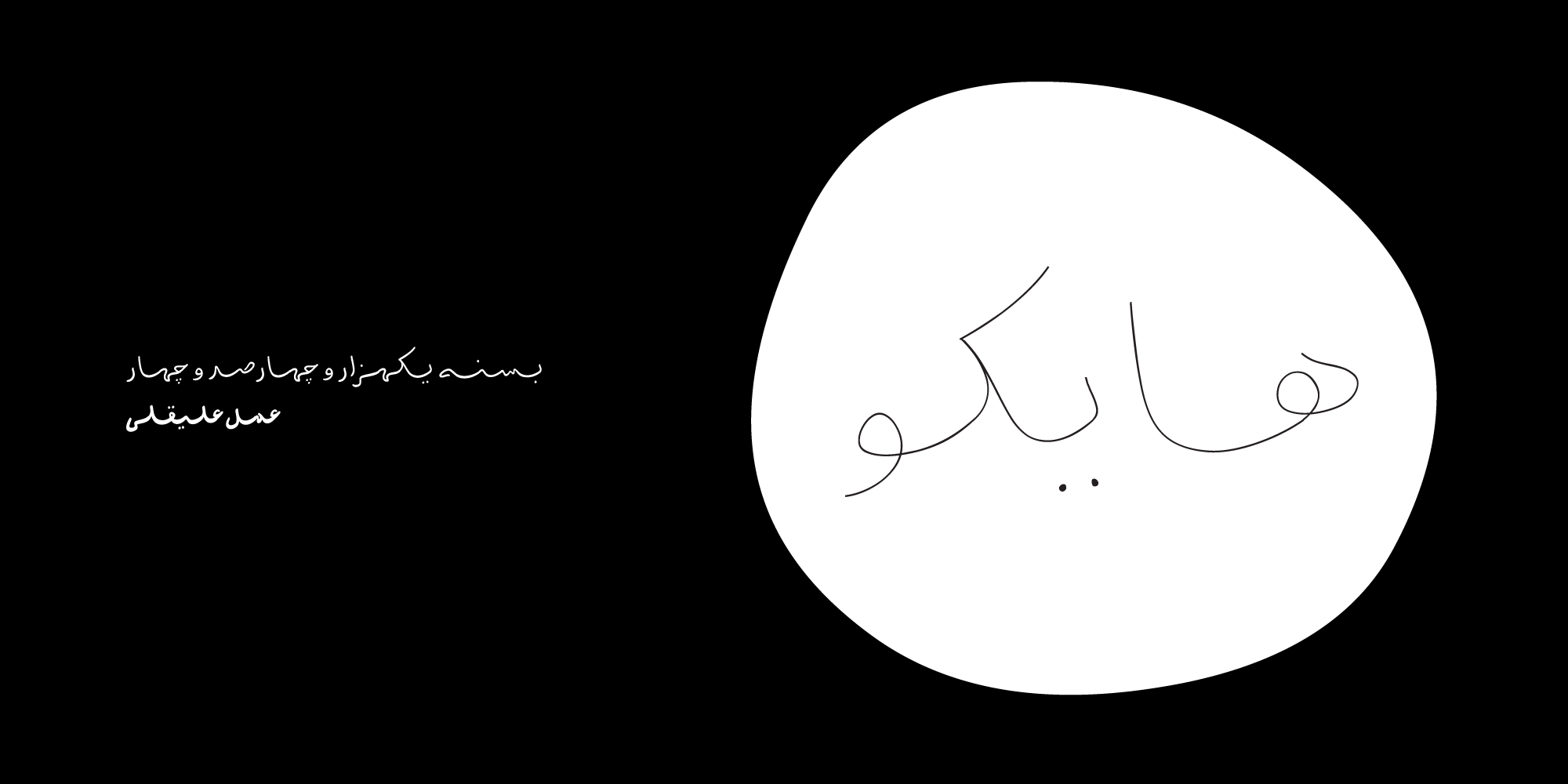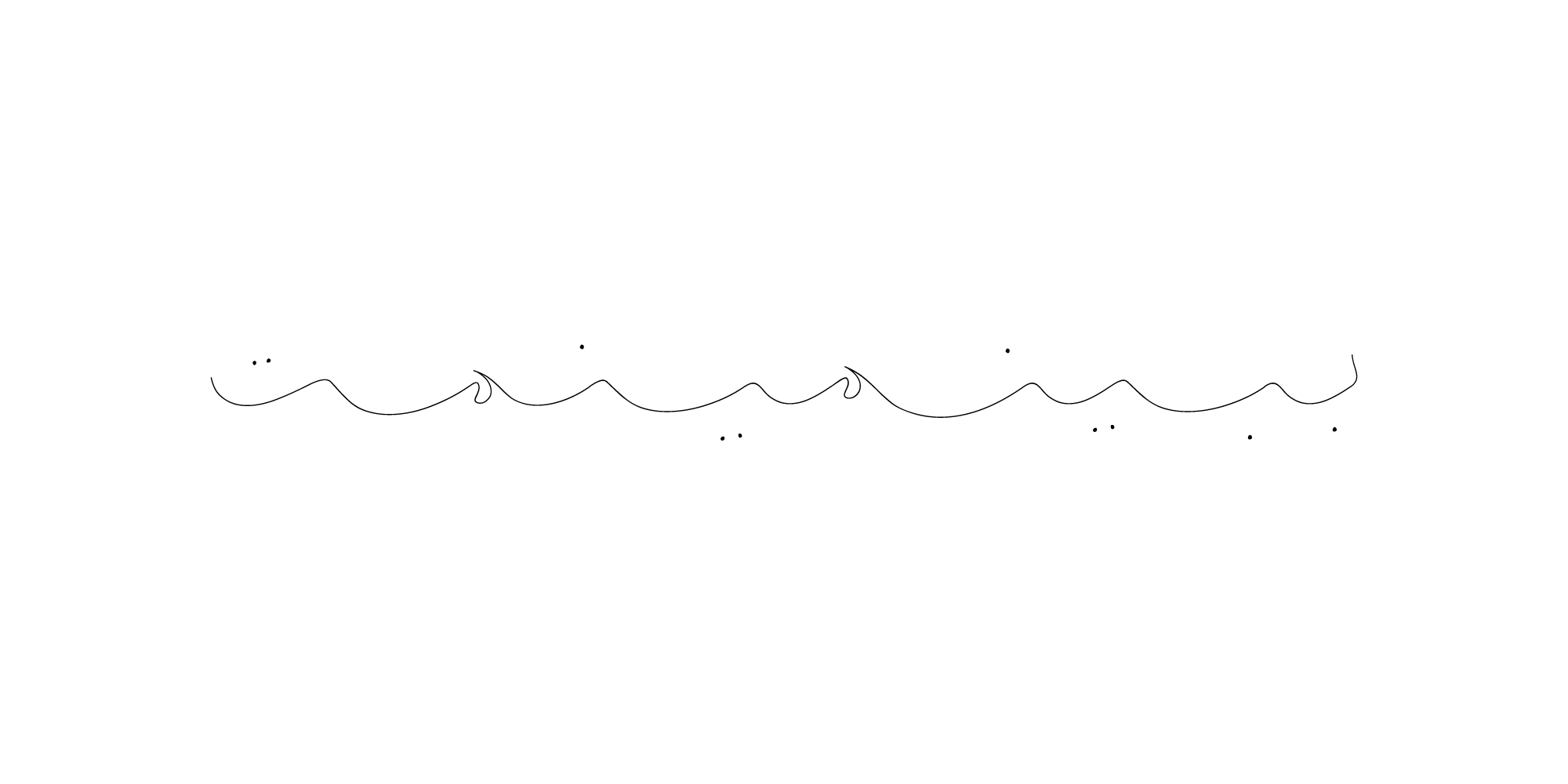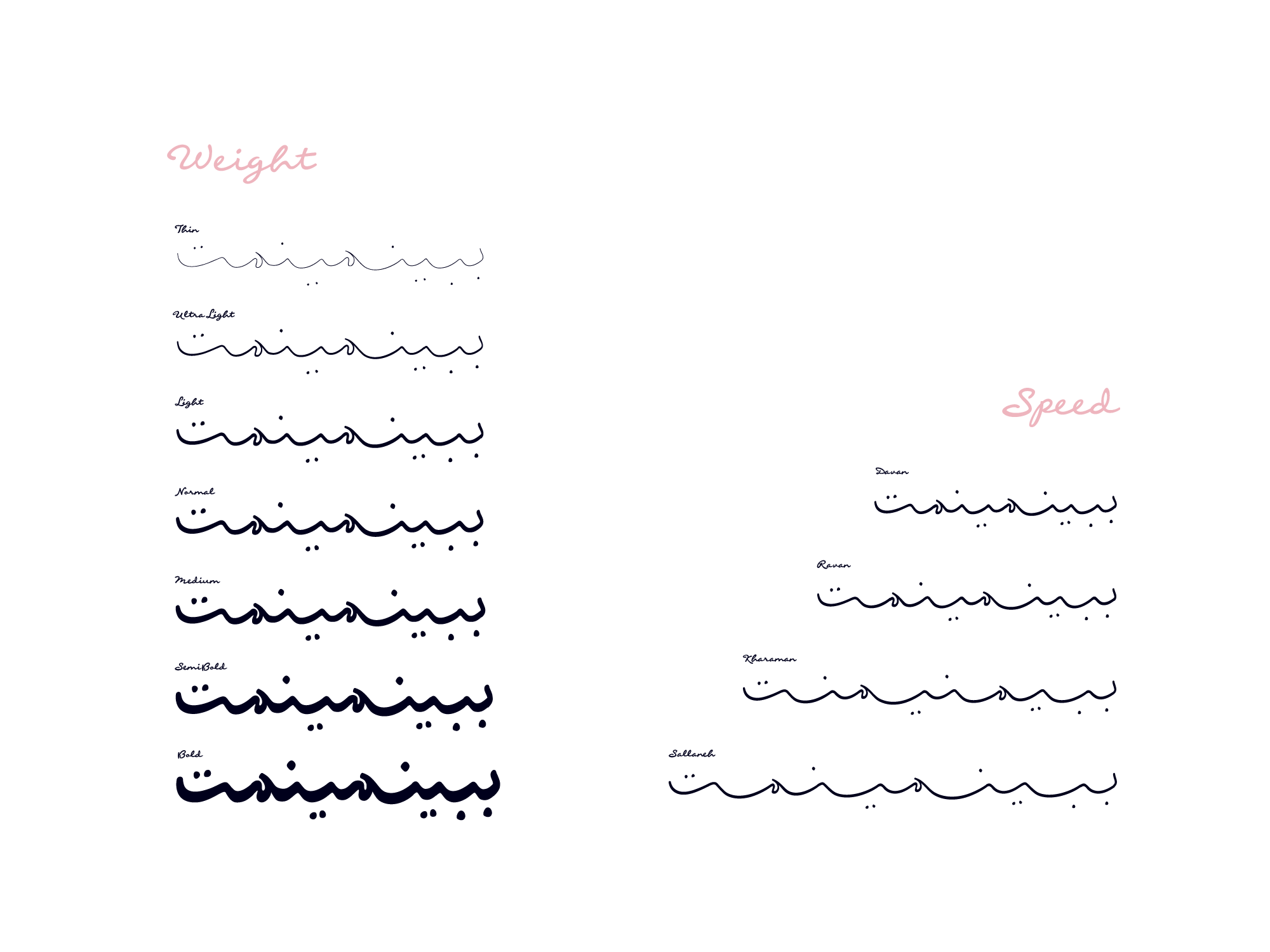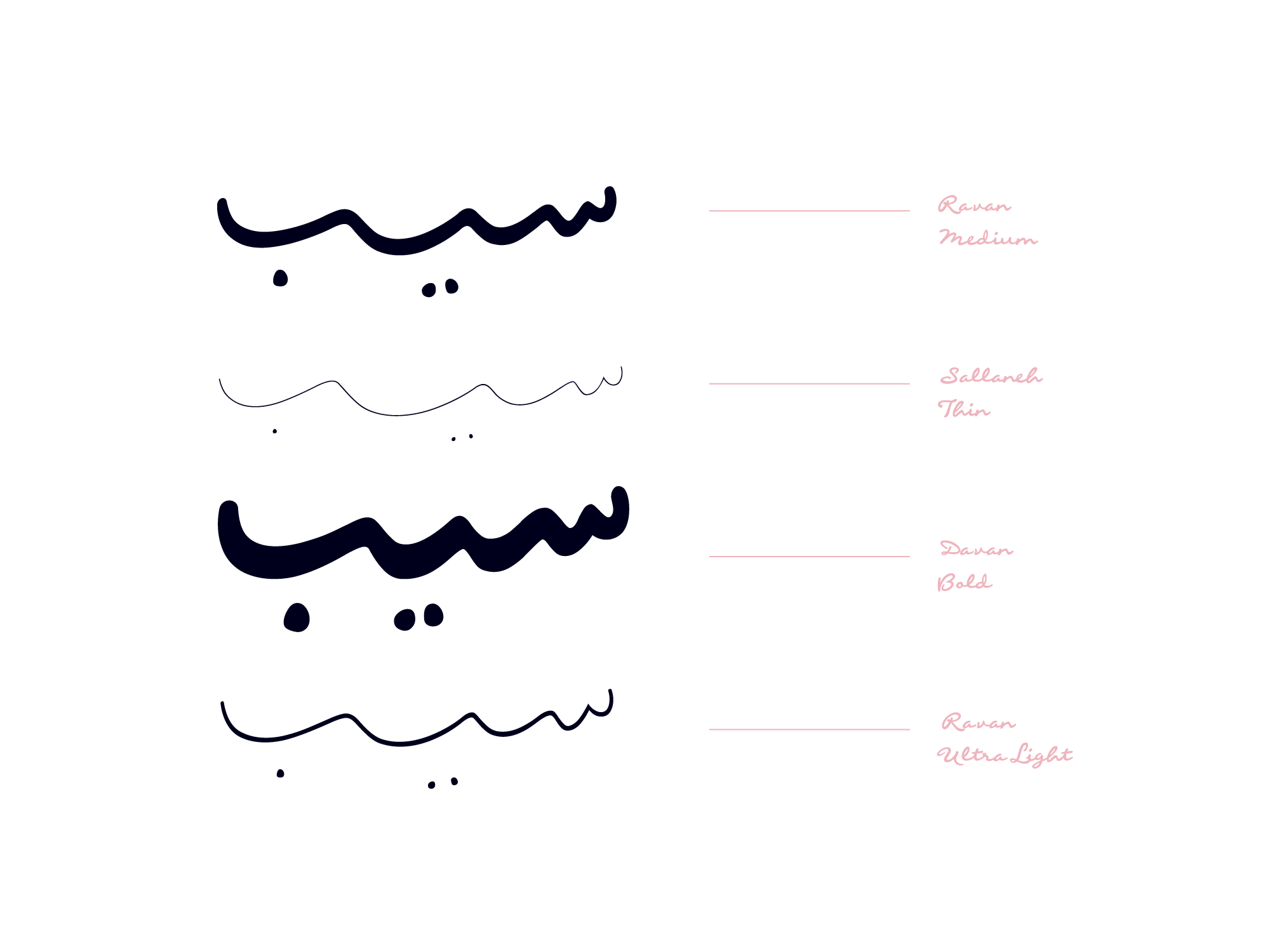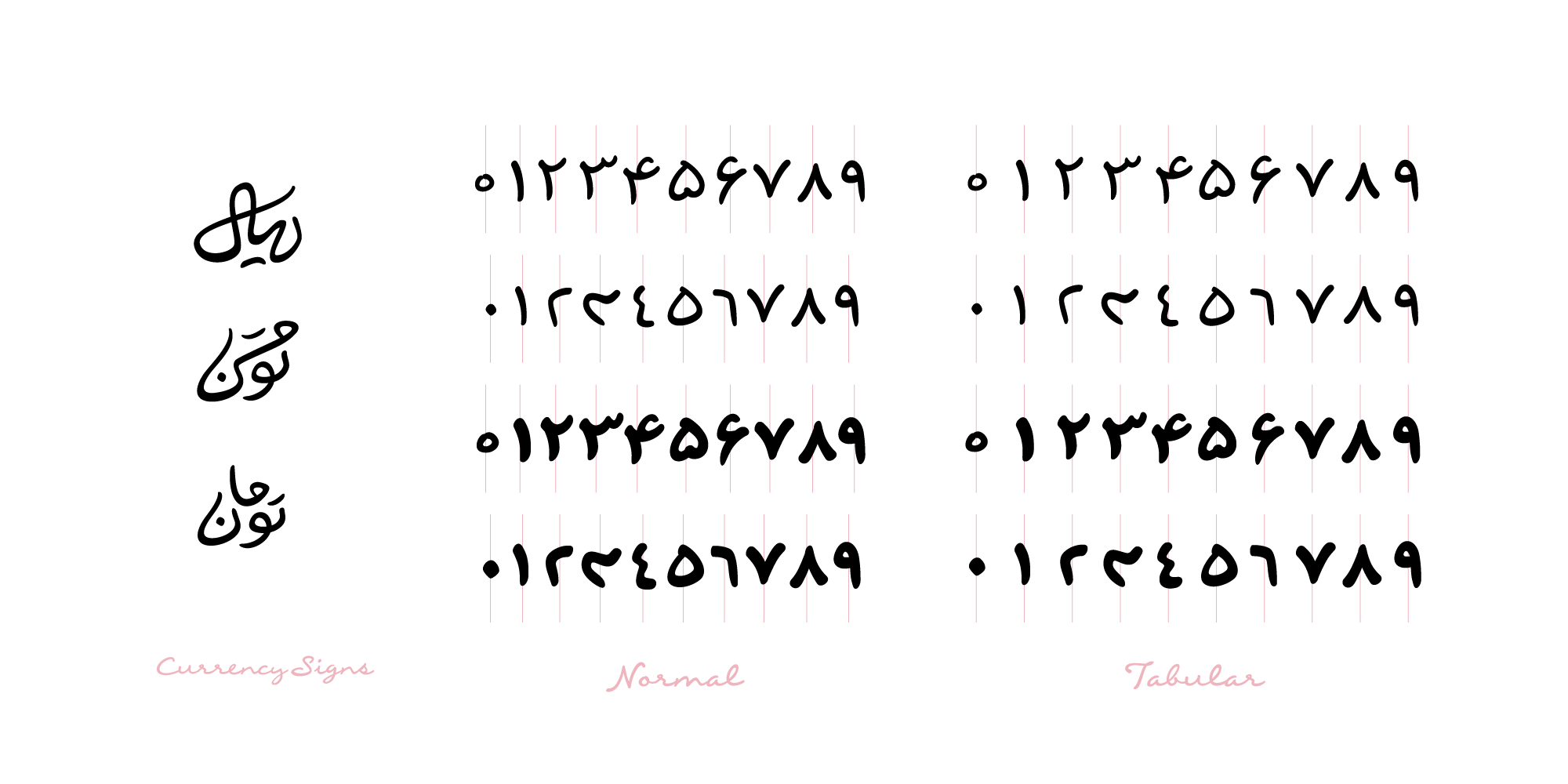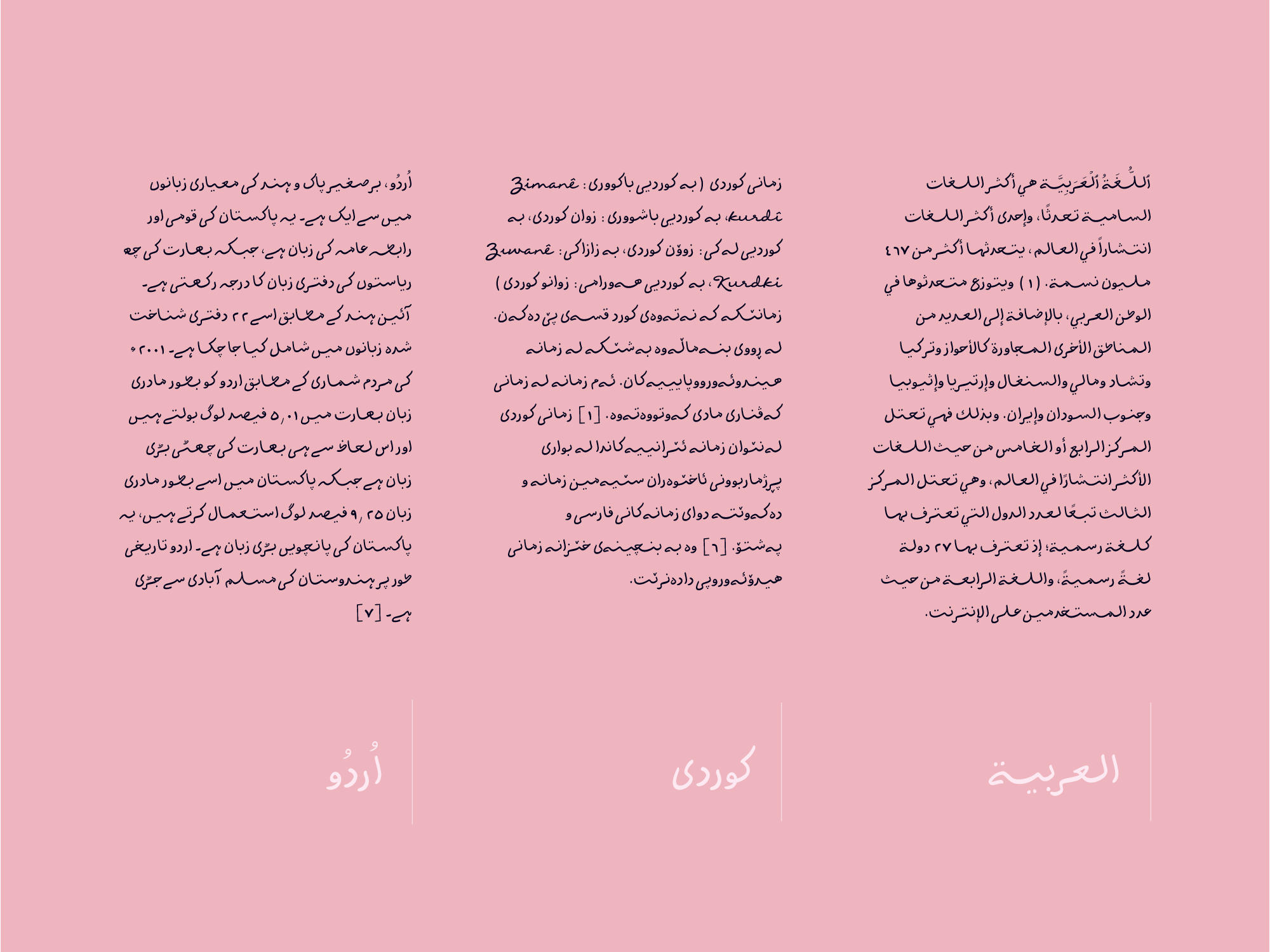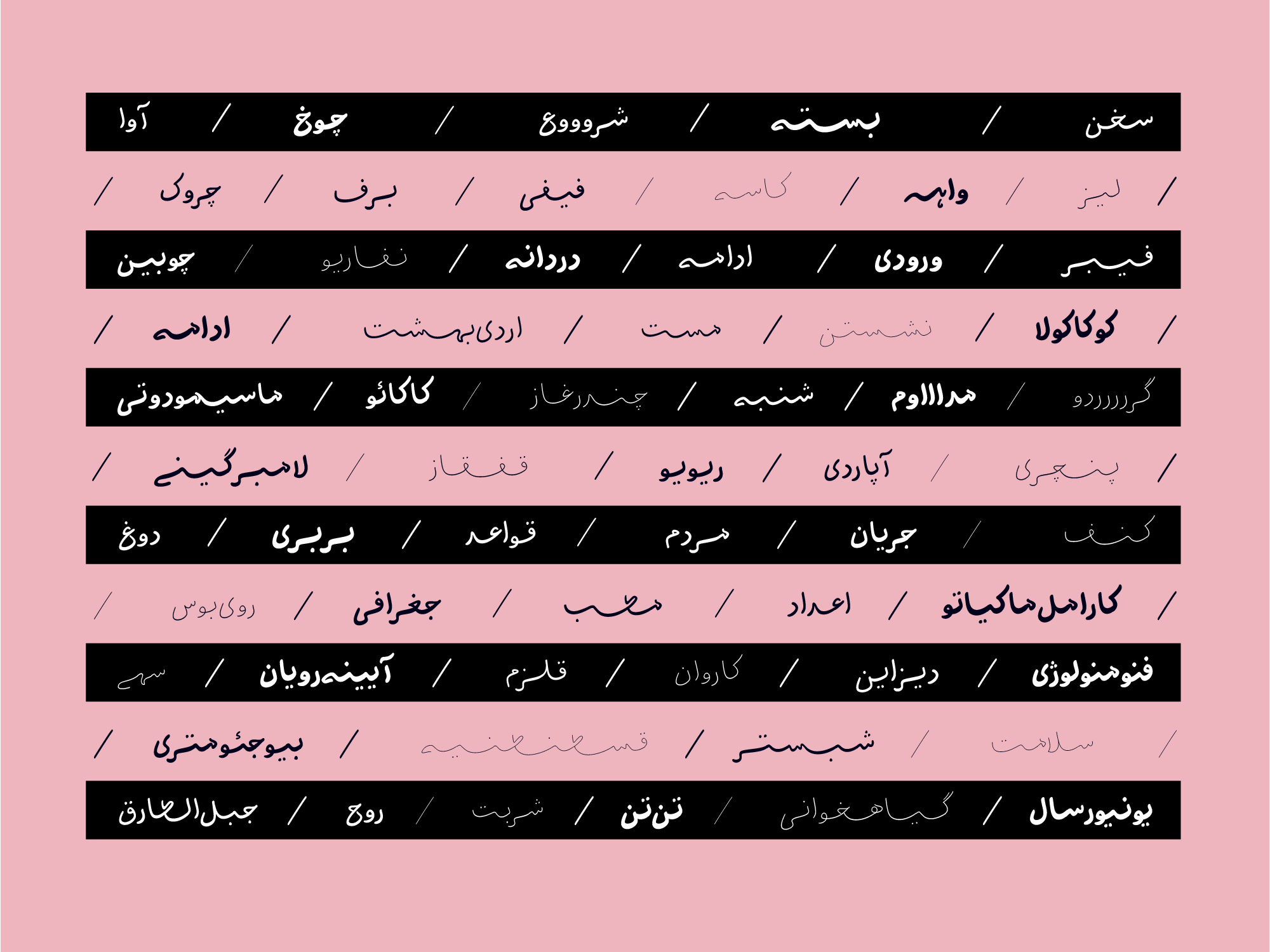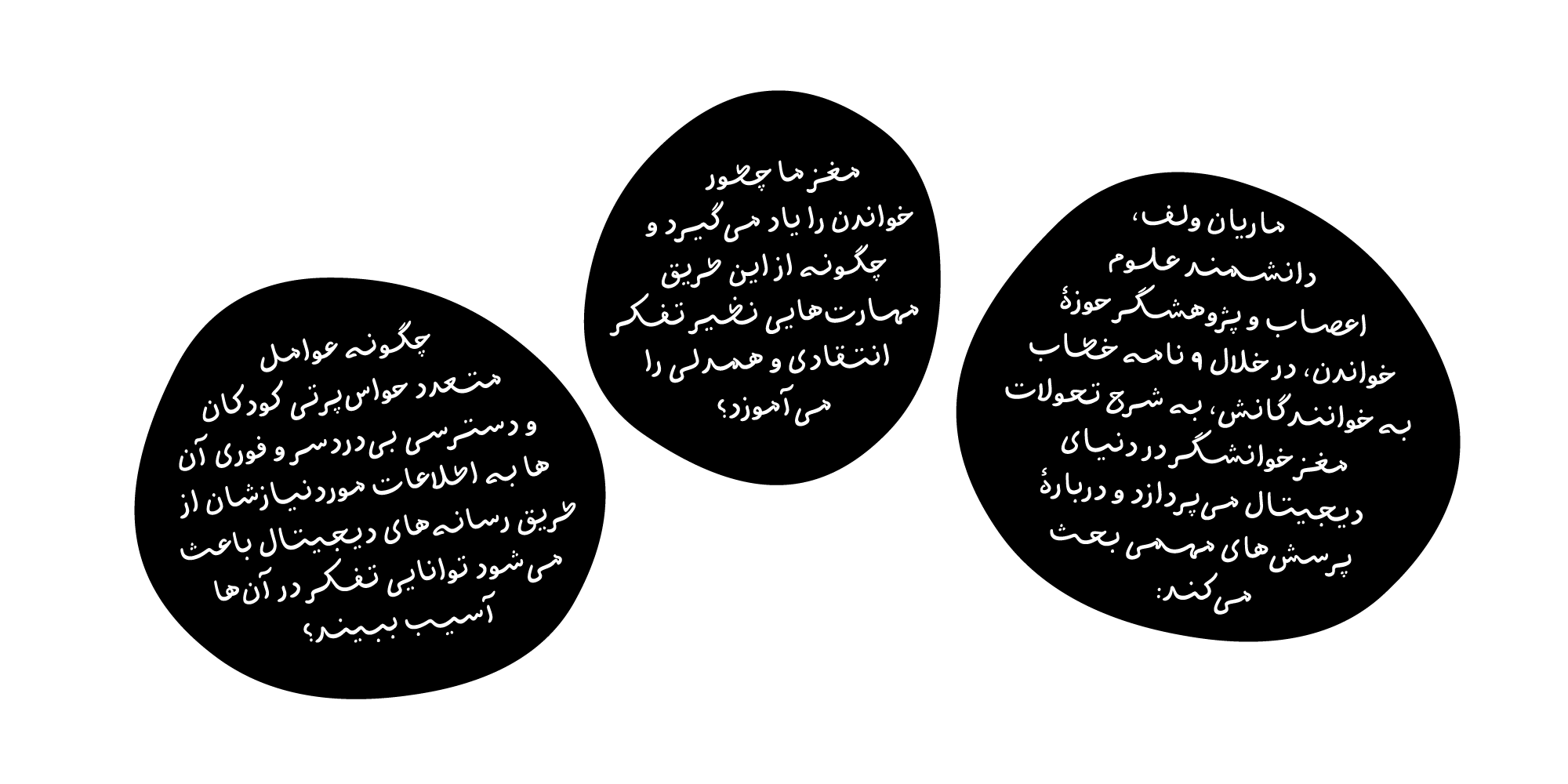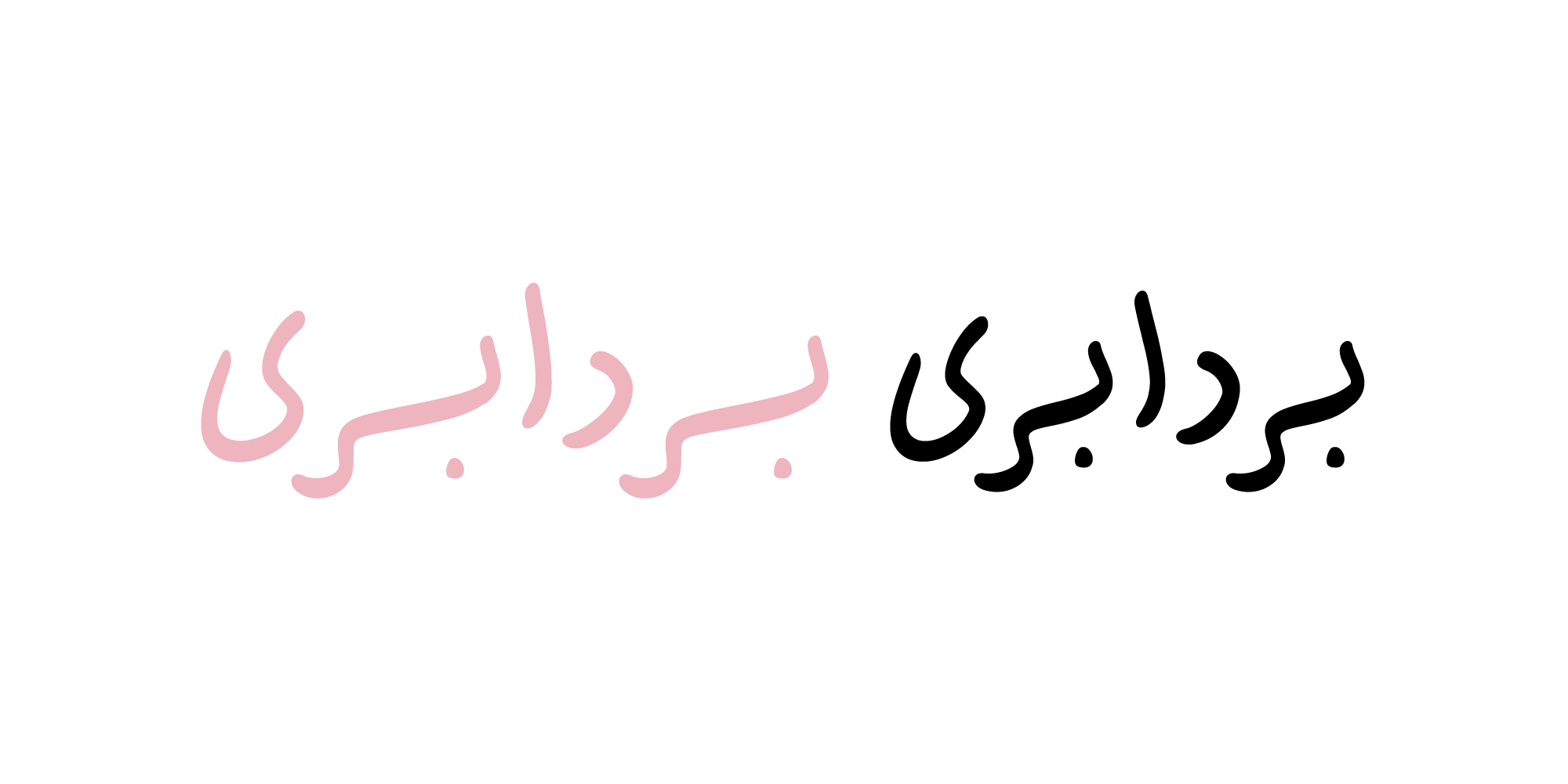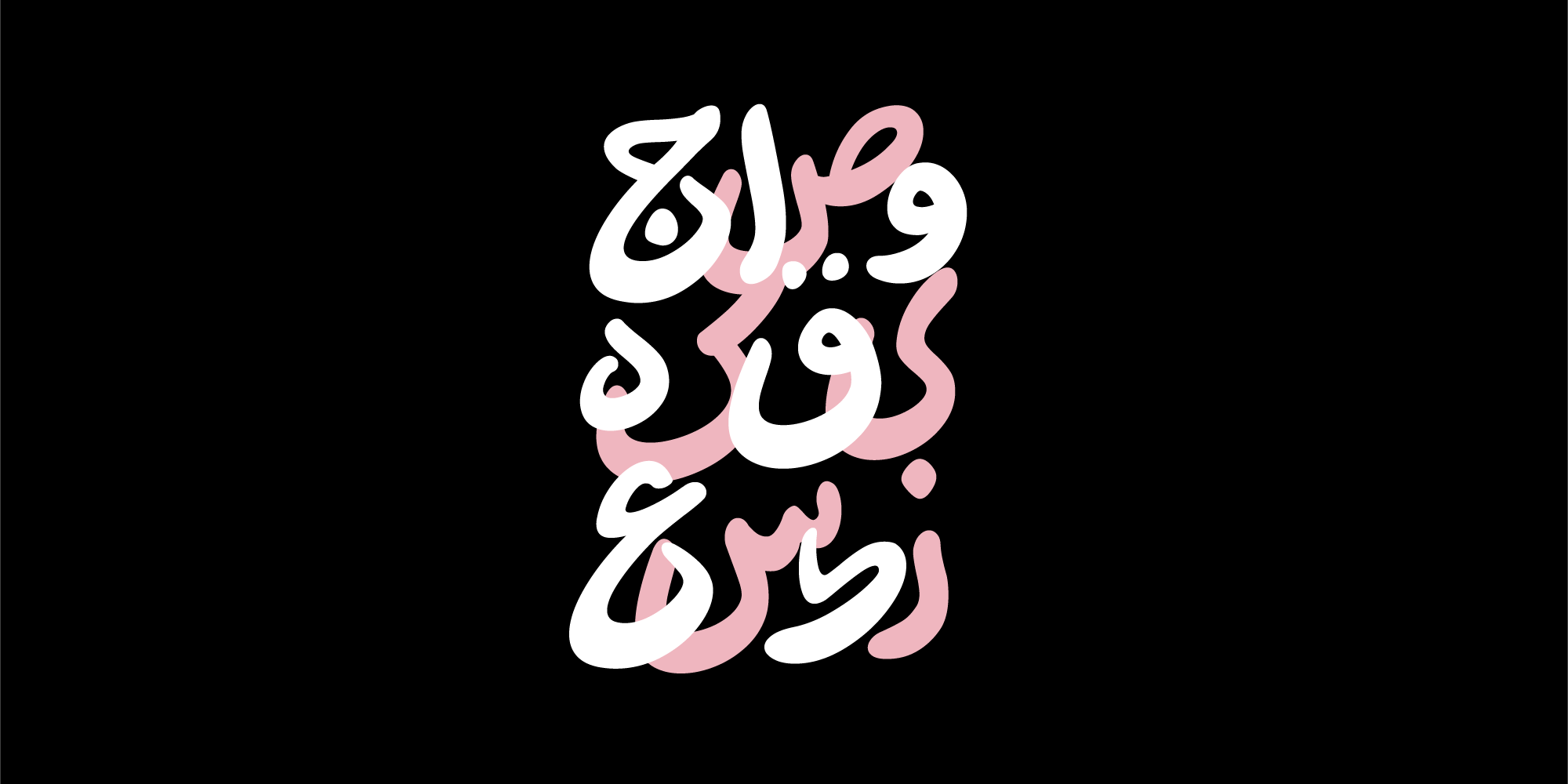
- وریبل فونت: فونتهای متغیر دارای ۲ محور (تغییر وزن و تغییر سرعت)
فونت هایکو دو محور تغییر دارد:
ضخامت (طیفی از مویی تا بولد) و سرعت (دوان/روان/خرامان/سلانه)
اعداد به شکل معمول و قابل استفاده در میان متن و به شکل همعرض قابل استفاده هستند و نشانههای ریال و تومان برای این نسخه فونت طراحی شدهاند.
هایکو از زبانهای عربی، کردی و اردو پشتیبانی میکند و برای متنهای چندزبانه کاراکترهای لاتین متناسب با کاراکترهای فارسی در آن اجرا شده است .
هایکو، کوتاهترین شعر ژاپنی است.